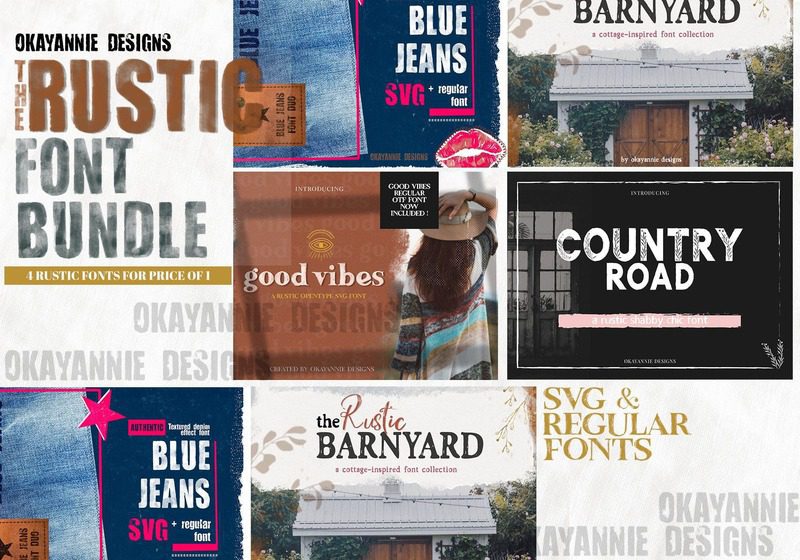
تقديم Rustic Font Bundle من تصميم OkayAnnie
حزمة Rustic Fonts هذه مخصصة لأولئك الذين يحبون الملمس واللعب بالخطوط ، وتوفر هذه الحزمة الفرصة لامتلاك مجموعة من أفضل الخطوط المنسوجة لدي لإنشاء قطع فنية ريفية مذهلة.
تتضمن حزمة الخطوط الريفية من تصميم OkayAnnie ما يلي:
· Blue Jeans SVG و Regular Font – 5772567 – مجموعة واحدة × خط أبجدي وأرقام وعلامات تنقيط قياسي SVG (otf) ومجموعة واحدة × خط أبجدي وأرقام وعلامات تنقيط عادي
· Good Vibes SVG and Regular Font – 5165065 – الأبجدية القياسية والأرقام وعلامات الترقيم الخط النقطي SVG (otf) ومجموعة واحدة × الأبجدية القياسية والأرقام وعلامات الترقيم خط OTF العادي * ملفات TTF
· مكافأة المشاعر الجيدة – رسومات الشعار المبتكرة البوهيمية – 37 عنصرًا رسوميًا بتنسيقات Photoshop و PNG
· طريق البلد | Rustic Font- 3 191482– 1 مجموعة x قياسية الأبجدية والأرقام وعلامات الترقيم الخط العادي (otf) ومجموعة واحدة x الأبجدية القياسية والأرقام وعلامات الترقيم خط الأزهار OTF
· خط Rustic Barnyard 3660111 – مجموعة Rustic مع مجموعة كاملة من الأحرف الكبيرة والصغيرة والأرقام وبعض علامات الترقيم والبدائل والأحرف المركبة ودعم الأحرف الدولية – ملفات OTF و TTF
خط Barnyard مع مجموعة كاملة من الأحرف الكبيرة والصغيرة والأرقام وعلامات الترقيم والدعم الدولي – ملفات OTF و TTF